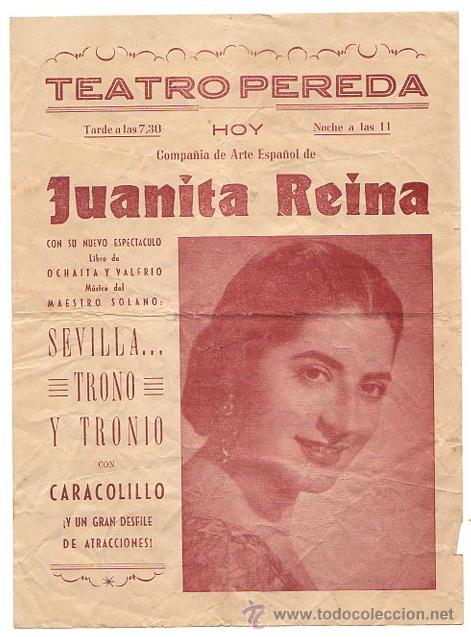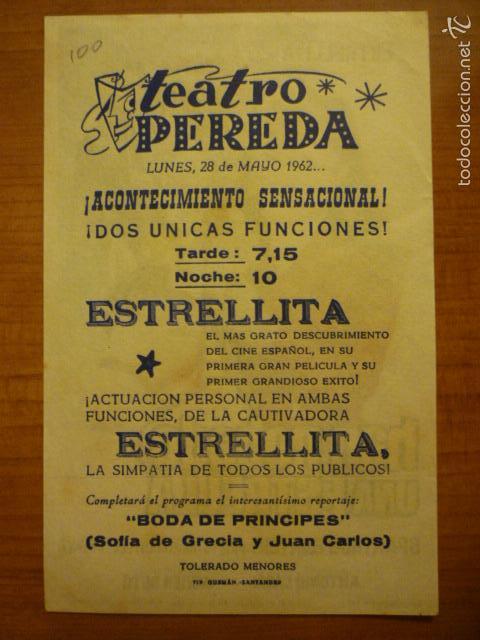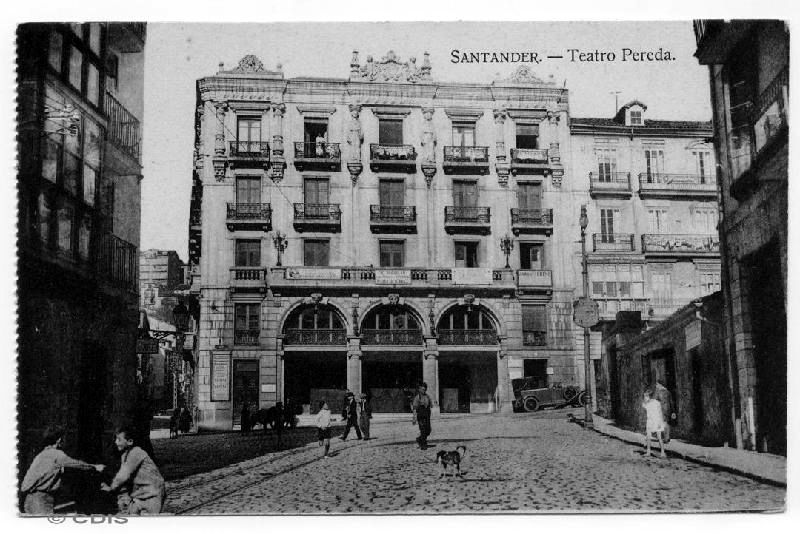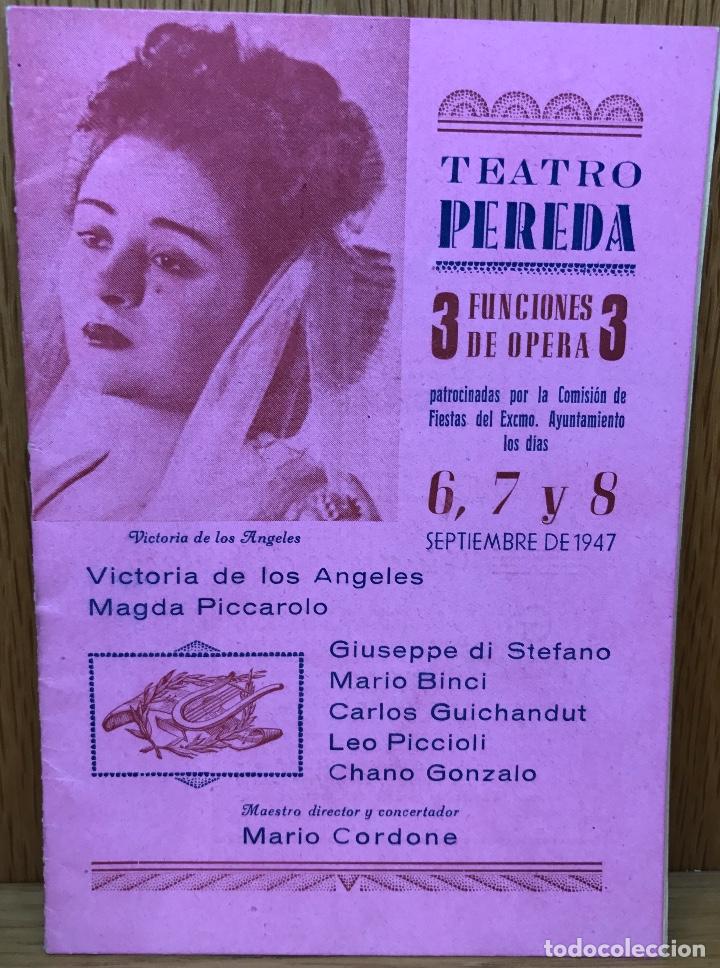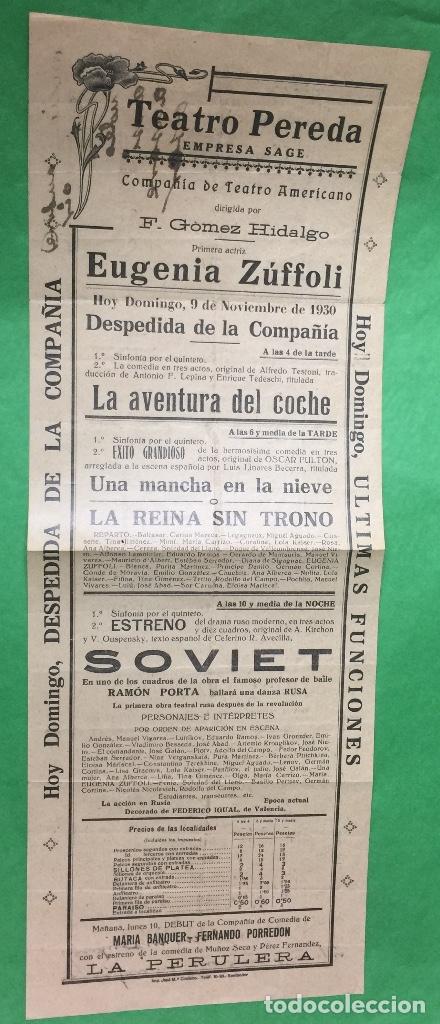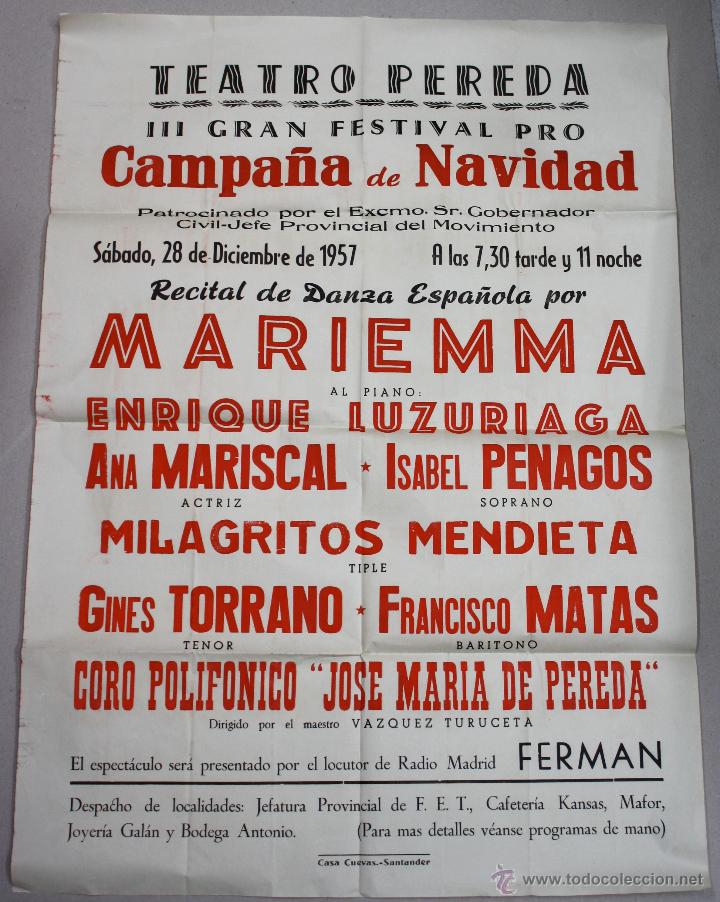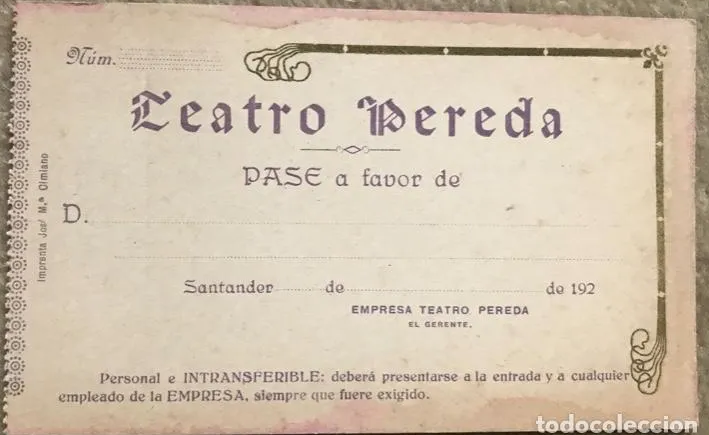
Teatro Pereda
El 1 de julio de 1919 se inauguró un Teatro referente en la vida cultural de Santander: el Teatro Pereda. Estaba situado en la esquina de Santa Lucía con el Río de la Pila. Fue un edificio clásico, proyectado por Eloy Martínez del Valle e inspirándose en la Zarzuela de Madrid. Con 5 plantas y con capacidad para 1700 personas (600 en el patio de butacas, 310 en el anfiteatro y 700 en el «Paraiso») Tenía uno de los escenario más grandes de España, con un sistema manual de cambio de escenas, pero sobre todo destacaba por su espectacular acústica.
Por el pasaron las grandes figuras de la música y el teatro de aquellos años, fue Cine, tuvo circo y acogió en su último año de vida el Festival Internacional de Santander. el 31 de agosto de 1966 comenzaría su derribo. Ayer, 1 de Julio de 2019 hubiese celebrado su Centenario.
Fachada principal del Teatro al final de la calle Martillo (foto: Centro de Documentación de la Imagen de Santander, CDIS).
Como se puede observar en la imagen, no se puede ver rótulo que identifique el edificio. Es por ello que a lo largo de su historia sea frecuente ver diversos programas o carteles con distintas imágenes gráficas (como se puede ver en las páginas de coleccionismo).
La escogida para ilustrar esta entrada y recuperación es del año 1957, sacada de un cartel para un Festival de Navidad. De algún modo mantiene una semejanza a la tipo de la primera imagen (1947) con esos dibujos lineales en el cuerpo de las letras.